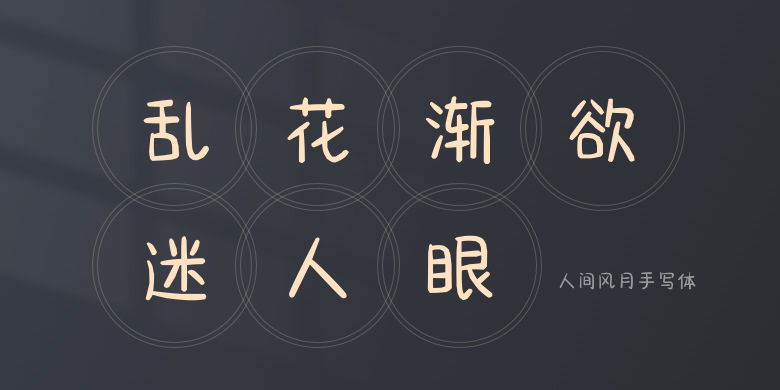
人间风月手写体
人间风月手写体,这款字体结构工整、笔画清晰,兼顾美观与易读性,适用于标题、正文、海报、包装、LOGO 等多种场景。字形优雅稳定,风格百搭耐看,适配日常排版与创意设计,让文字呈现更舒适、更具质感。人间风月手写体一笔一画,皆是细节,以均衡的比例、流畅的线条打造舒适视觉体验,字形端正大气,风格简约现代。无论是商业设计、品牌宣传还是日常排版,都能轻松驾驭,让文字更有格调与力量。人间风月手写体字体下载。